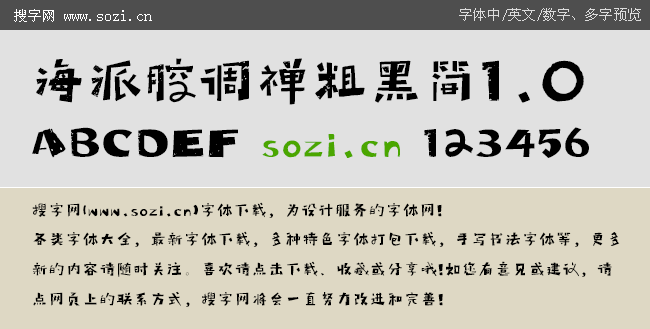
海派腔調(diào)禪粗黑簡(jiǎn)1.0
搜字網(wǎng)提供一款海派腔調(diào)禪粗黑簡(jiǎn)1.0中文字體下載,海派腔調(diào)禪粗黑簡(jiǎn)字體是一款左粗右細(xì)、整體效果非常出眾的簡(jiǎn)體中文字體,適合應(yīng)用于廣告設(shè)計(jì)、名片設(shè)計(jì)、包裝印刷、產(chǎn)品設(shè)計(jì)等應(yīng)用。
- 風(fēng)格類(lèi)別: 海報(bào)POP體